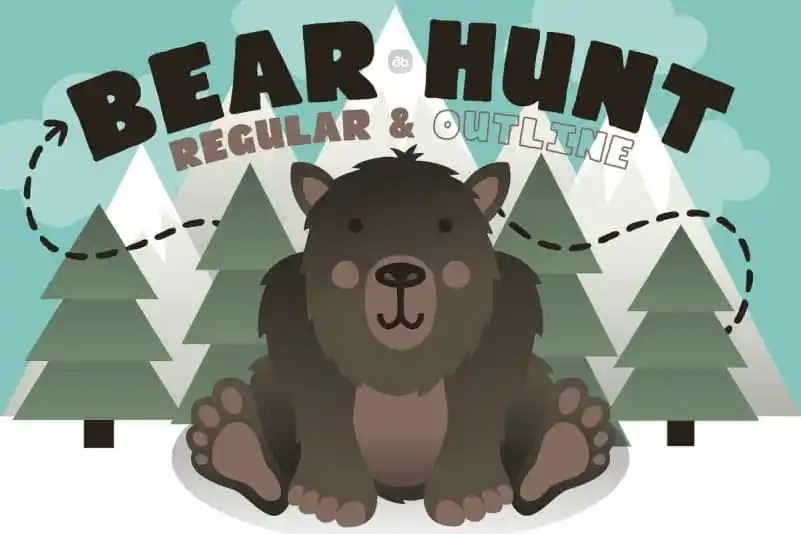
Introduzimos uma nova fonte de exibição “Bear Hunt Display Font”, inspirada no livro infantil “We’re Going on a Bear Hunt” do autor Michael Rosen. Desenvolvida para um projeto especial, foi criada como parte de designs de roupas pensados especialmente para sua filha que pode usá-la na creche. A fonte tem uma escrita livremente inspirada em livros ilustrados no estilo simples nórdico. Esta fonte retrata a personagem do urso e o ambiente, criado de forma minimalista e autêntica, tornando-a ideal para ambientes que valorizam um toque artístico. A “Bear Hunt Display Font” é uma combinação perfeita de estética infantil com uma personalidade forte, garantindo um toque diferente em projetos de design, seja ele impresso ou digital. Como qualquer fonte de exibição, ela traz modernidade e originalidade a qualquer projeto visual que você desejar. Não hesite em explorar como esta nova font pode moldar seu próximo trabalho!